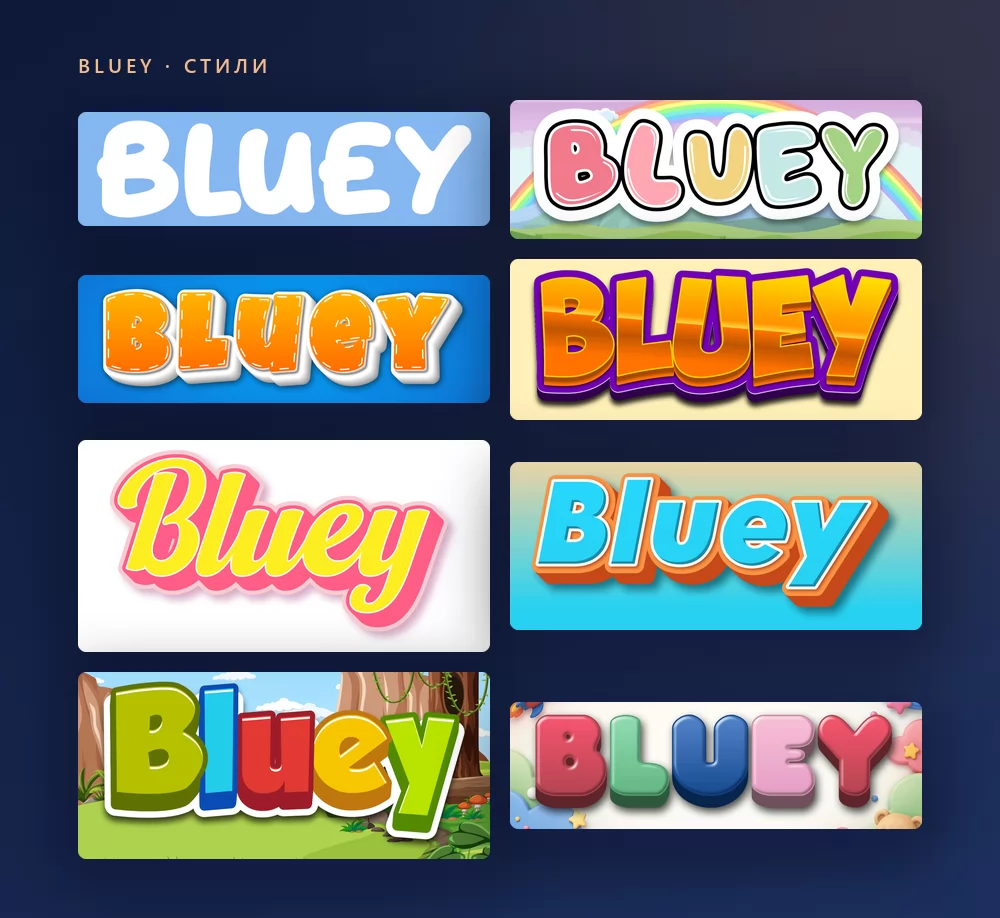
Все они сделаны одним и тем же генератором шрифта Bluey, только с другим стилем из списка. Ничего не нужно устанавливать, без регистрации.
О шрифте Bluey
Bluey («Блуи») это австралийский мультсериал для дошкольников, придуманный Джо Бруммом и созданный студией Ludo Studio в Брисбене. Он вышел на ABC Kids в 2018 году и разошёлся по миру через BBC Studios и Disney+. Это истории о Блуи, шестилетнем щенке породы австралийский хилер, её младшей сестре Бинго и родителях Бандите и Чили, чьи игры в воображаемые миры каждый раз оборачиваются жизненным уроком и для взрослых у экрана.
Логотип сериала это надпись, нарисованная на заказ: толстые, округлые, подпрыгивающие прописные, созданные для шоу и никогда не выпускавшиеся как шрифт. Везде в остальном, в заставке, титрах и на официальном сайте, используется Hello Headline, шрифт Венеты Рангеловой, выпущенный DearType. Когда в 2023 году вышла Bluey: The Videogame, слова «The Videogame» под логотипом тоже были набраны Hello Headline. Это коммерческий шрифт.
Из бесплатных шрифтов с похожим видом сайты, стоящие по этому запросу в выдаче, называют одни и те же три: Blue Custard от rockcake, а также Lovely Bubbles и Magical Markers от Даррелла Флада. Heyam от FG Studios это второй близкий коммерческий вариант.
Как сделать текст в стиле Bluey
Шаг 1. Введите имя
Откройте генератор и замените пример своим текстом: имя ребёнка, «С днём рождения», табличка для класса. Буквы перерисовываются прямо во время набора. Стиль сам делает всё прописными, как в логотипе.
Шаг 2. Выберите стиль
Классика это толстые белые округлые прописные на небесно-голубом. На вкладке «Стили» заливка, обводка и тень меняются отдельно, так что подпрыгивающие буквы можно оставить, а цвета увести в другую сторону: оранжевый для праздника в стиле Бинго, бледно-розовый, радуга.
Шаг 3. Выберите формат
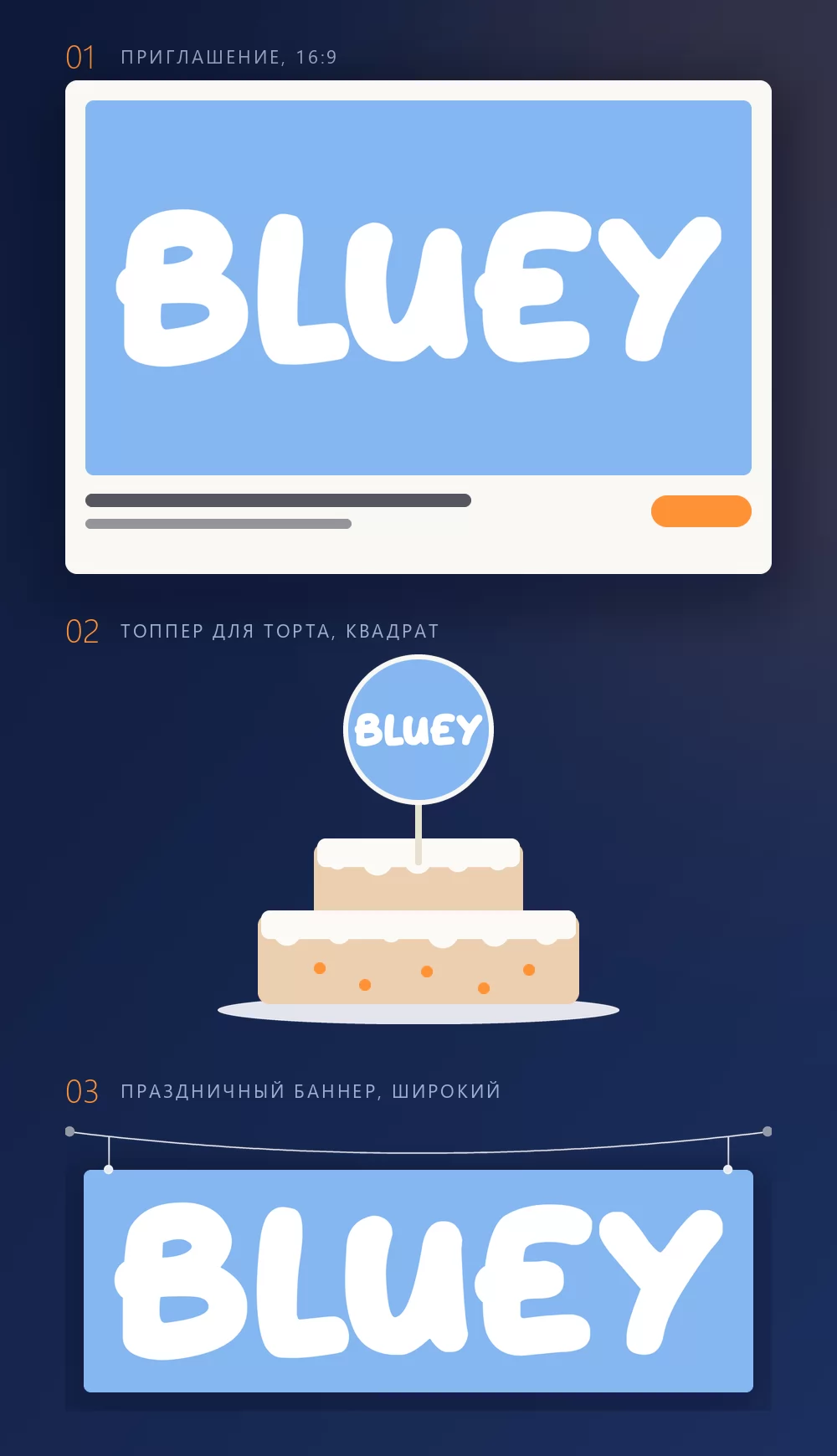
Задайте формат до экспорта, и потом ничего обрезать не придётся. 16:9 для приглашения, квадрат для топпера на торт или капкейк, широкая полоса для баннера через всю стену. Три макета выше показывают, во что превращаются эти форматы после печати.
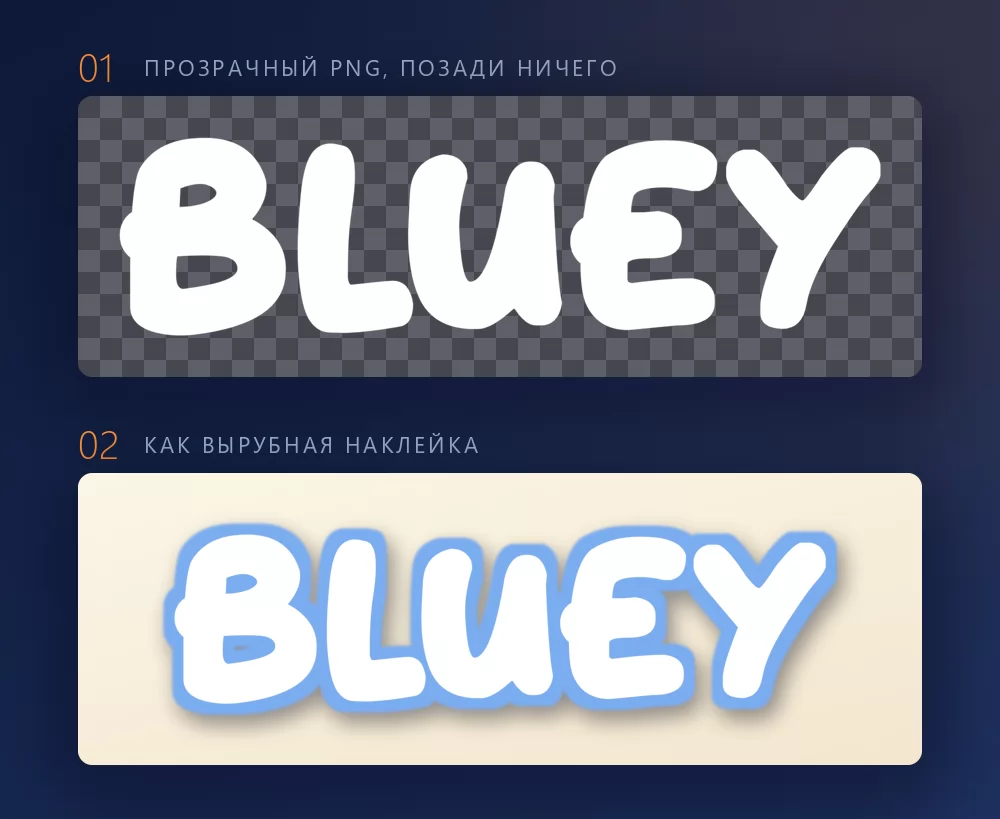
На вкладке «Скачать» берите прозрачный PNG, если собираетесь положить имя на свой макет. Эту опцию большинство пропускает, а для праздничной печати именно она и важна: ваша бумага, имя сверху, никакой синей рамки вокруг. Это же нужно и режущему плоттеру для вырубной наклейки или топпера: форма букв это форма реза.
Длинные имена быстро заполняют ширину
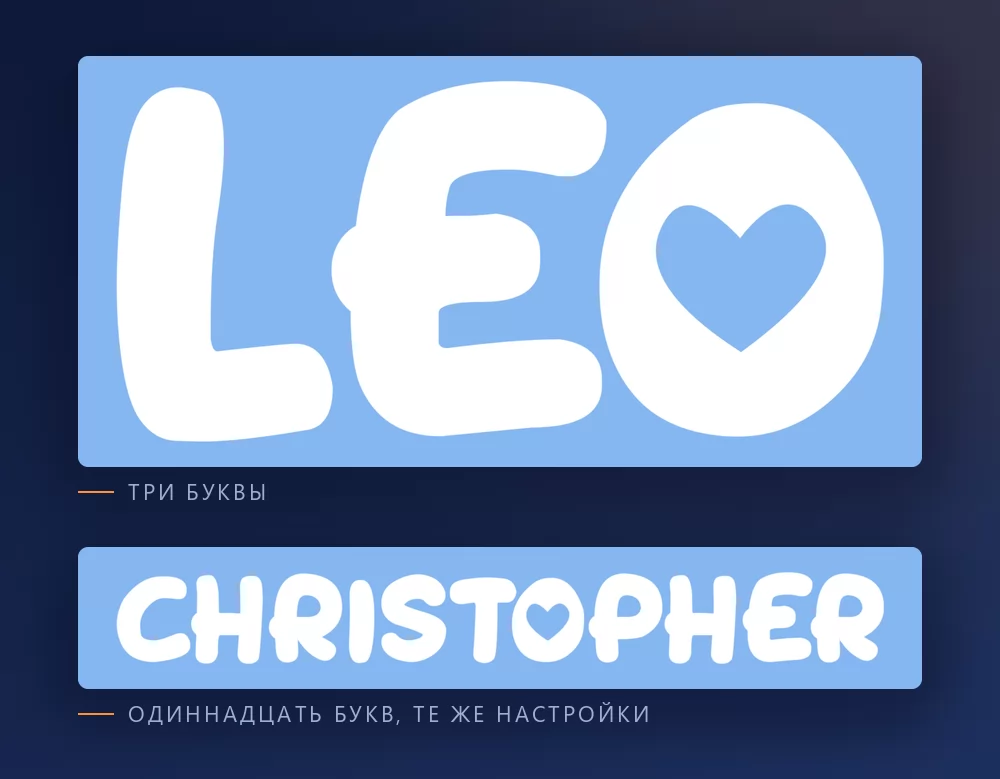
Чем больше букв, тем плотнее они сидят. Межбуквенный интервал это ползунок на вкладке «Текст»: чуть раздвиньте, и длинное имя перестанет выглядеть сжатым. На той же вкладке масштаб, межстрочный интервал, изгиб и поворот.
Стиль Bluey или стиль игровой комнаты
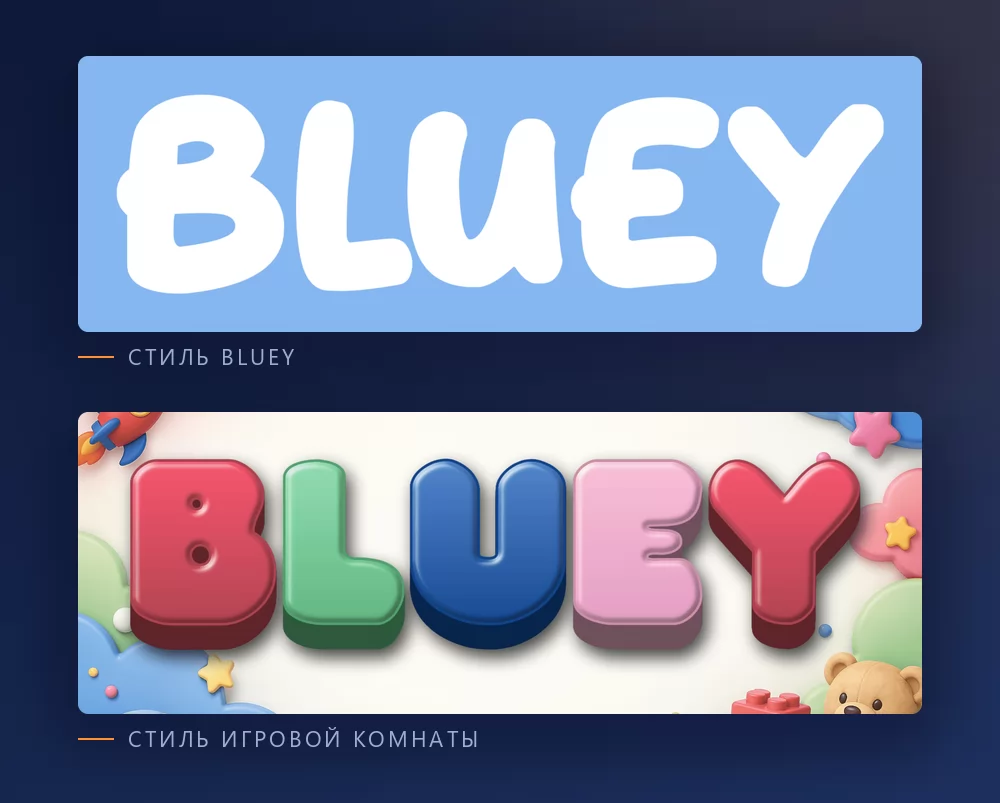
Стиль Bluey это сам логотип: белый, толстый, округлый, чуть подпрыгивающий, на том самом небесно-голубом. Именно это большинство представляет, и именно это нужно дню рождения в стиле Блуи.
Стиль игровой комнаты это округлые пластиковые буквы пастельных цветов с разбросанными вокруг игрушками. В нём нет символики сериала, и потому он лучше подходит для стены детской или первого дня рождения без темы. В генераторе букв игровой комнаты он есть как готовый стиль.
Какой шрифт, если вы хотите его установить
Сам логотип это не шрифт. Это надпись, нарисованная на заказ, поэтому любой файл с названием «шрифт Bluey» является чьим-то воссозданием.
Hello Headline это настоящий ответ для всего остального в сериале. Коммерческий шрифт DearType, который покупают и скачивают у студии. Если нужен точный вид заставки и титров, это он.
Blue Custard от rockcake это бесплатный шрифт, ближе всего подходящий к подпрыгивающим прописным логотипа. Он лежит на DaFont как donationware: пользоваться можно свободно, а автору будут рады чаевым.
Lovely Bubbles и Magical Markers, оба от Даррелла Флада, это два других шрифта из любого списка. Lovely Bubbles указан как бесплатный для личного использования, Magical Markers как donationware, оба на DaFont.
Для работы с клиентами, где лицензия должна быть чистой, честные варианты это округлые шрифты с открытой лицензией на Google Fonts: Fredoka, самый близкий по духу, с полным набором начертаний, Baloo 2 и Sniglet. Ни один из них не шрифт Bluey. Все три дают дружелюбный округлый вид с лицензией, которую никто не оспорит, и все они доступны в Canva.
Что с ним делают на самом деле
Страницы скачивания перечисляют «лучшие применения», и они совпадают с тем, что действительно делают: приглашения на день рождения, топперы на торт и капкейки, баннеры через всю стену, бейджи с именами для праздника, футболка для именинника, таблички для класса и приветственные вывески. Почти всё это печатается, и почти всё лучше работает с прозрачным PNG, чем с установленным шрифтом, потому что вид это белые буквы на том самом небесно-голубом, а файл шрифта даёт только контуры.
Почему мой текст выглядит не так рядом с настоящим логотипом? Обычно дело в голубом, а не в шрифте. Логотип стоит на светлом, чуть сероватом небесно-голубом. На ярком электрическом синем или с градиентом он перестаёт читаться как Bluey.